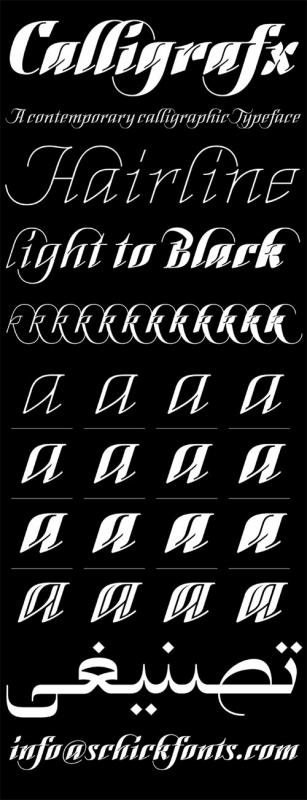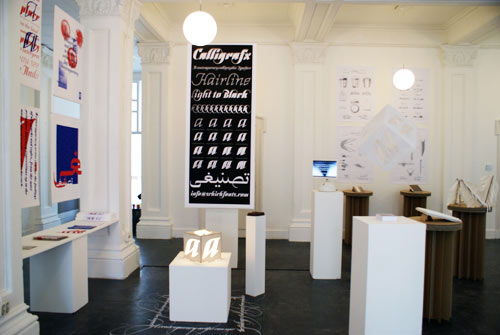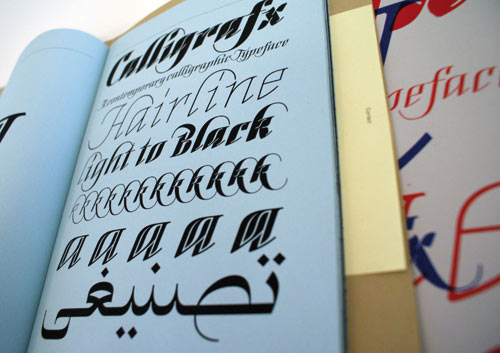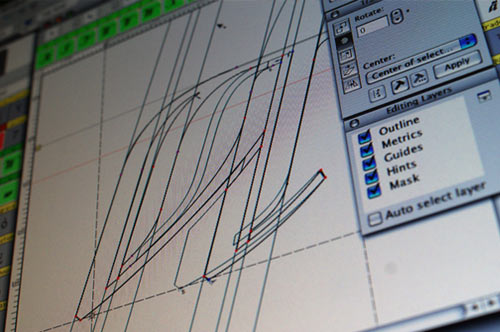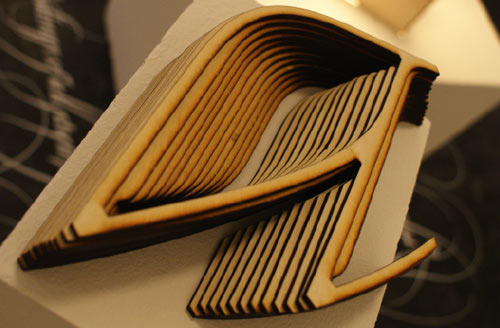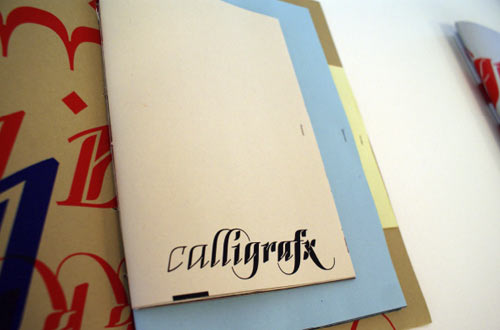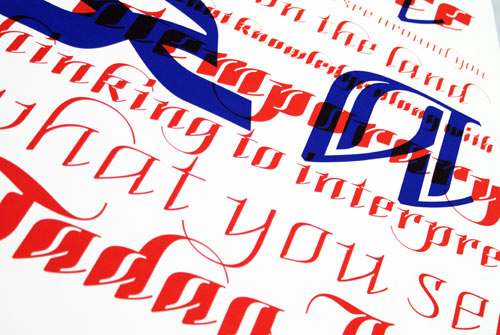
Florian Schick hat an der Royal Academy of Art (Den Haag) eine kalligrafisch anmutende Schrift als Bachelorarbeit entwickelt. Der Titel seiner Arbeit lautet, »Calligrafx a contemporary calligraphic typeface« und wurde betreut durch Gert Dumbar, Reza Abedini, Peter Verheul und Kees van Drongelen.
Calligrafx bedient sich Features aus verschiedensten Epochen und Buchstabenstilen. Geschwungene kalligrafische Elemente, Inktraps aus dem Bleisatz, fanden hier genauso Verwendung wie Konstruktivismus und Streetart und geben der Schrift ihren zeitgenössischen Karakter. Die Schrift enthält 12 Schnitte, die von sehr fein bis extrem fett reichen. Zusätzlich gibt es eine Inline Version in 6 Schnitten sowie die arabische Variante.